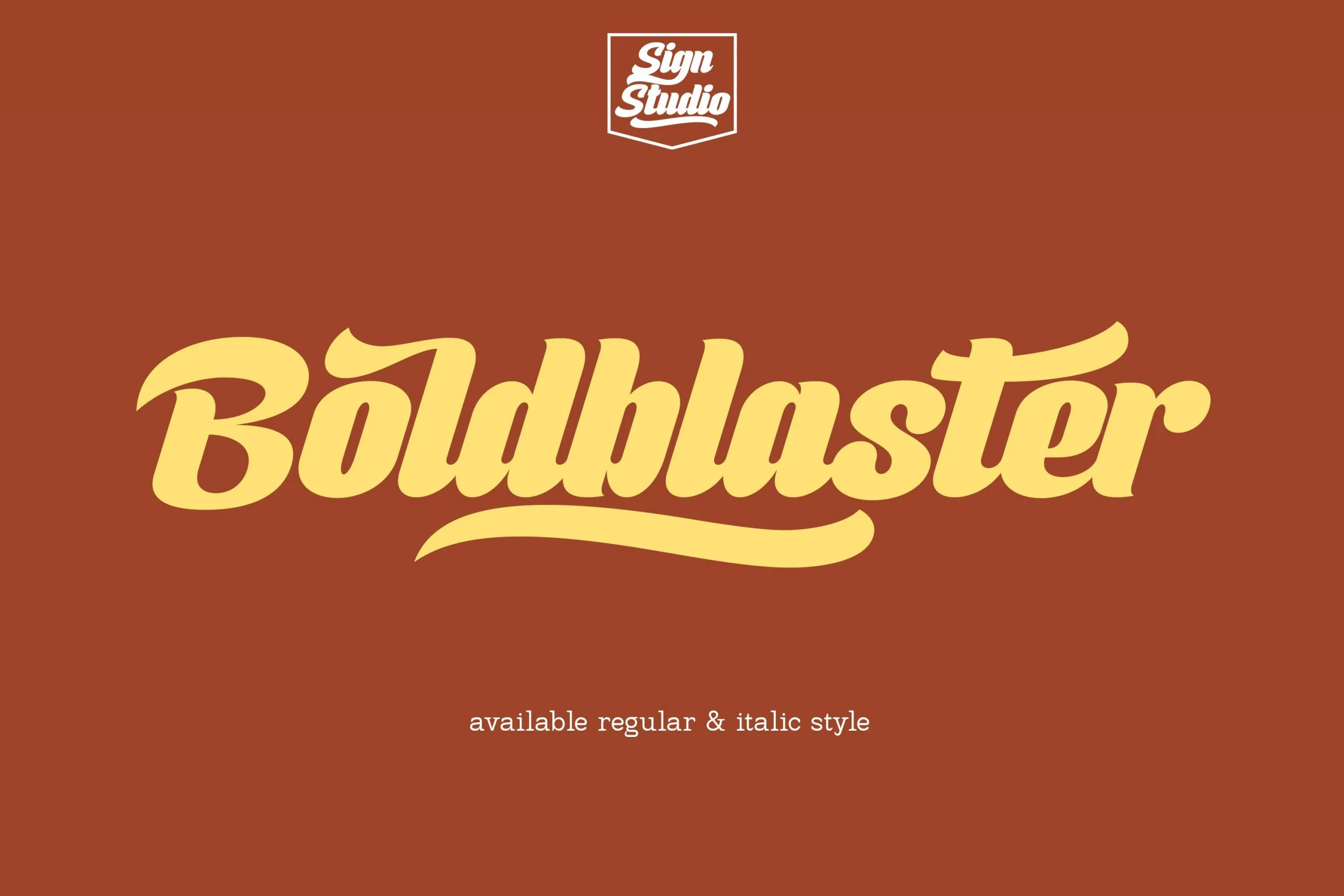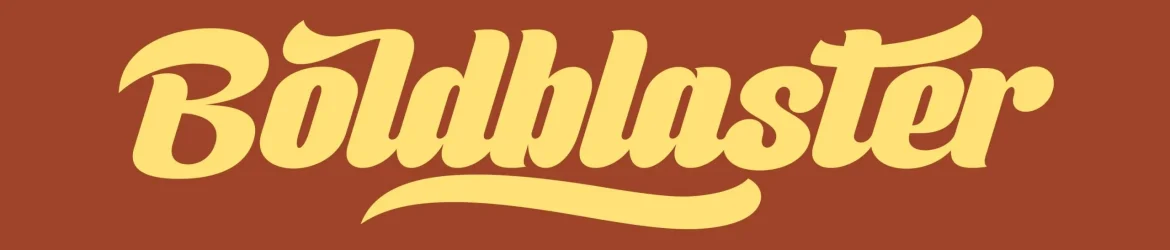
A Boldblaster Script Font é uma obra-prima perfeita para quem busca trazer à tona aquele clima nostálgico dos anos 70 em seus projetos digitais, seja no design de gráficos ou em criações web. Feita pelo designer Sign Studios, a Boldblaster encanta por sua aparição forte e confiante, fornecendo os elementos necessários para dar um tom retrô ao seu trabalho. Com mais de 250 caracteres disponíveis, incluindo swashes que permitem uma grande variedade em suas composições, esta fonte pode ser a solução perfeita para aqueles buscando adicionar cores nostálgicas e emoção aos seus designs. Além disso, ela é PUA (Unicode Plane X) encoded, permitindo um uso fluido de todos os símbolos e swashes sem nenhuma dificuldade. A Boldblaster Script Font não apenas oferece uma linguagem elegante para seu design, mas também traz a essência da cultura dos anos 70, tornando-a a escolha ideal para quem quer dar vida à sua criatividade através do design de fontes.